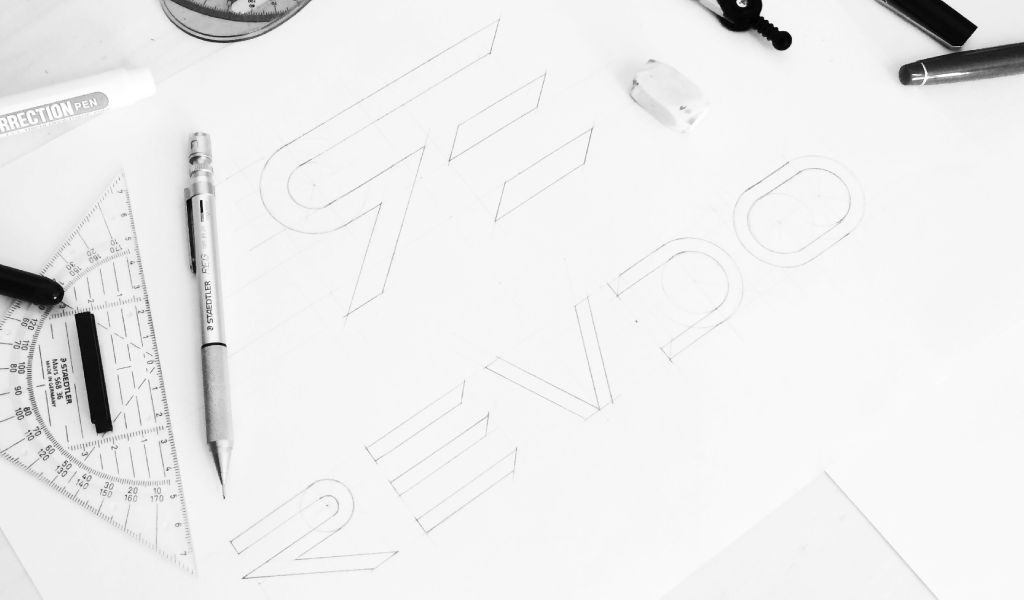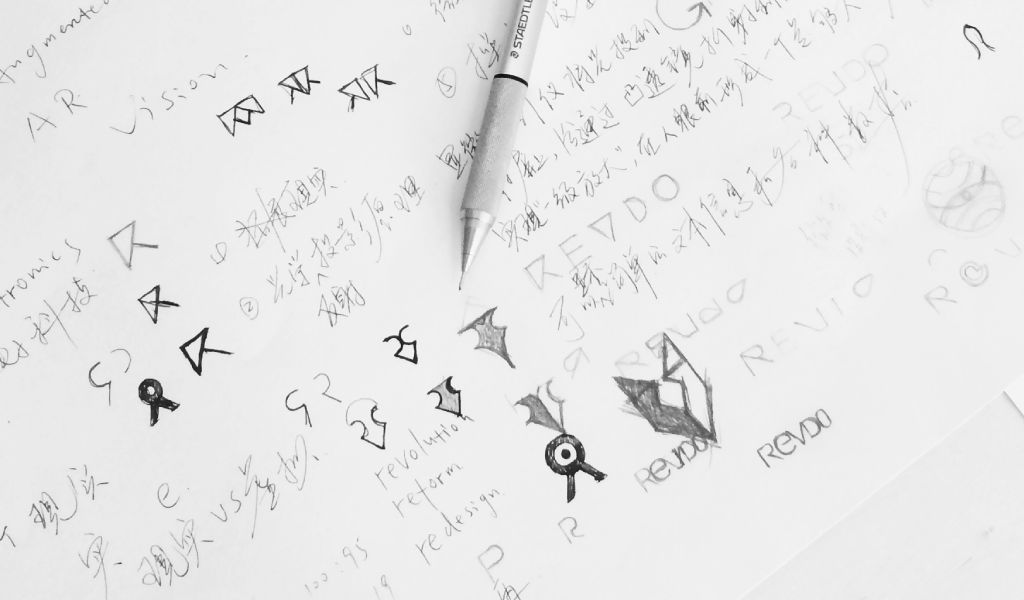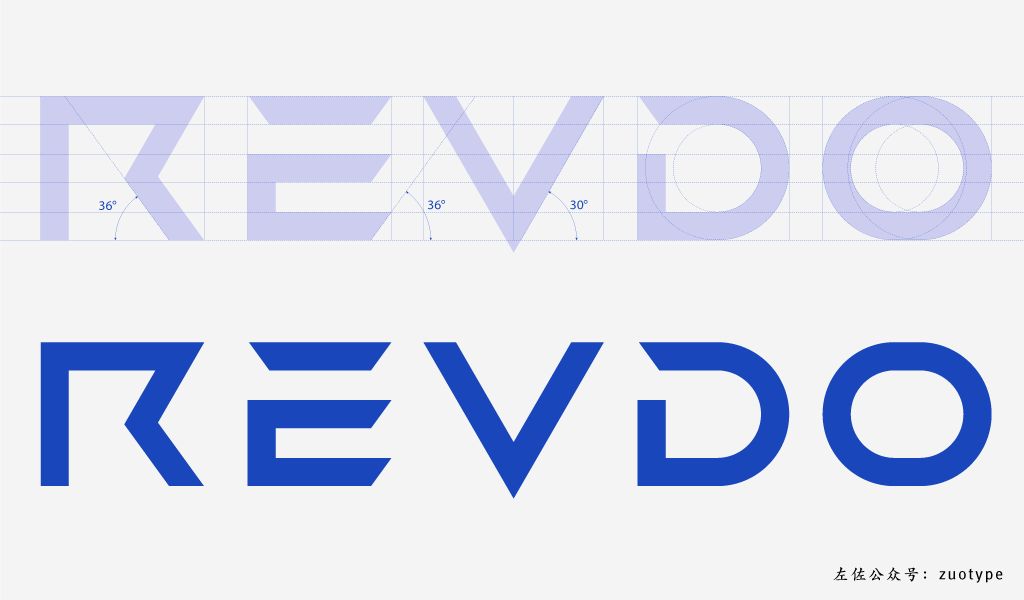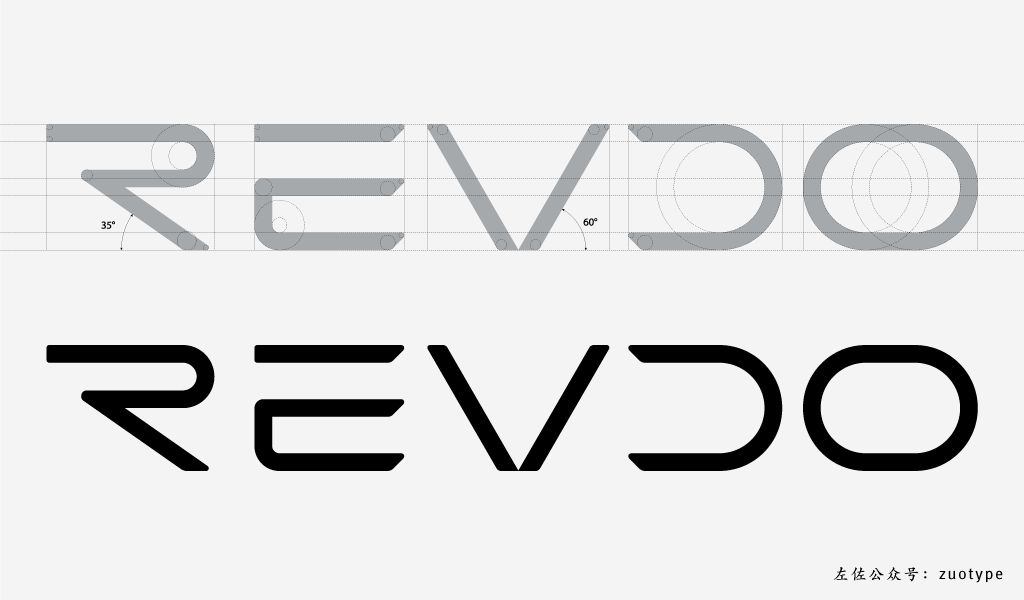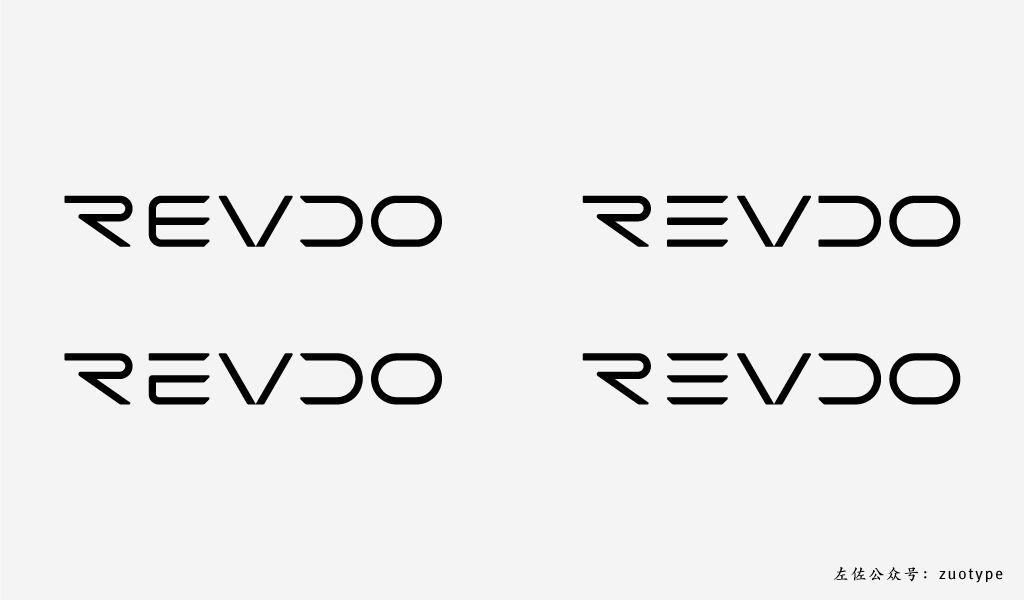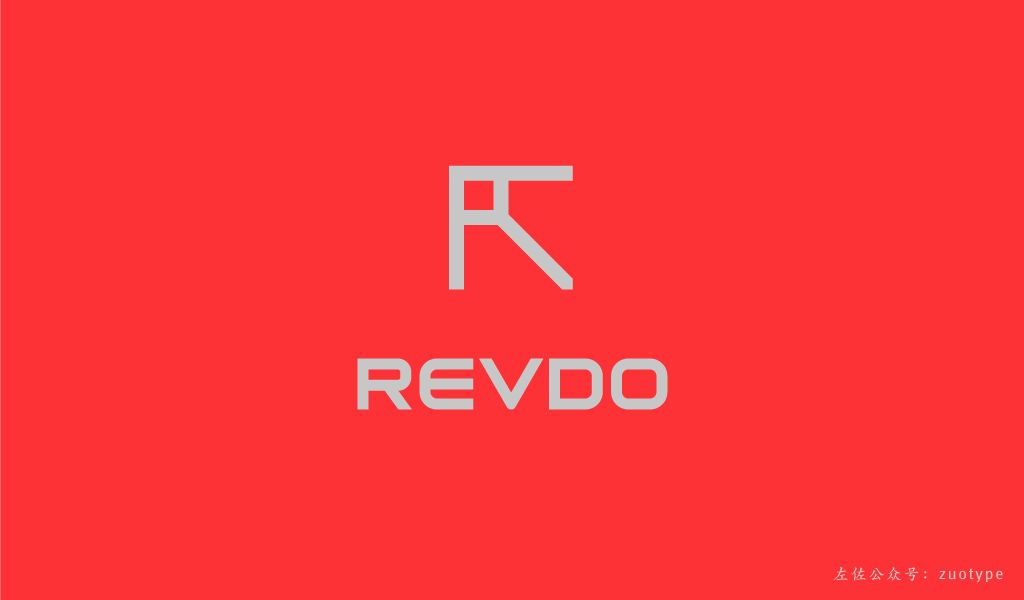
revdo,AR智能头盔品牌,抬头显示、后置摄像头、安卓系统等。rev是发动机每分钟的转速,re是重新设计的意思,do则是行动。
智能、科技、未来
从关键词出发,找到了一些横向领域的参考字形。比如美国头盔品牌Skully、谷歌眼镜GLASS、电影《安德的游戏》、美剧《星际迷航》等。
西文logo最常见的做法就是从首字母出发,结合关键词,联想名字带来的画面元素,或产品形的延伸,把这些信息通过字母这个载体传达出来。
从草稿里选择的几个方向,大前提是图形具有未来气质。类似这样简洁,且与智能相关的图形,我会在保证美观的前提下,尽量用数学去规范,因为任何科技最后都是数学。用“RE”的概念,重新定义、另一个方向,把“R”翻转,与“E”在形式上连接,并去掉各自的竖,形成一个新的图形元素。用“鲁宾杯”的负形手法,用互为镜像的“R”的外部空间,组合出一个新的图形元素,同样表达出重新定义、基于现在但又不同于现在的可能性。
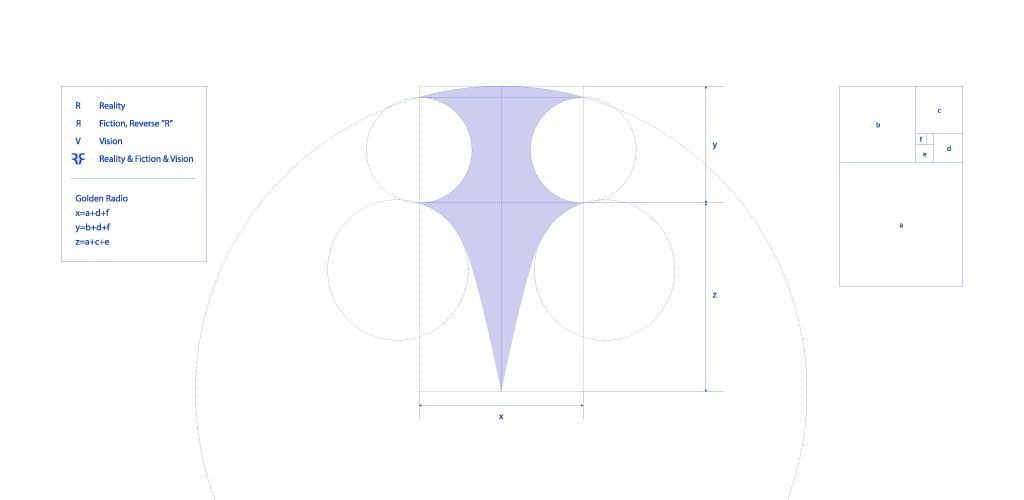
这个图形与特斯拉有些许类似,虽然之前并未参考,但对于简洁的图形来说,其实区别很明显,只是特斯拉太出名,最好还是规避一下,避免落人口实。所以降低了图形的高度,从深“V”变为圆领,视觉效果确实有折扣,所以宁可使用之前的版本。把技术上的现实增强,转化为抽象的图形,并与“R”结合,从一个小的方形,放大到一个大的方形空间,然后去掉边界,传达科技带来的无限可能性。什么样的西文具有未来科技感?一般来说,无衬线体,且是等线的,用几何图形组合而成,比如圆形、直线、直角等,然后字母有缺口、或有缺笔,字面偏扁,大写,不能过粗。
最直接的、最容易、最常见,但略带点复古,我管这种风格叫“诺基亚式”,《银翼杀手》《疯狂的麦克斯》《赛博朋克2077》可归于这一类。扁、圆角、中等粗细、等线。
之前在《机械姬》文章里提到过,常用小写字母,有温度,我管这种风格叫“仿生式”,《西部世界》《普罗米修斯》《异星灾变》可归为这一类。字母“e”用小写,且形式用螺旋线,字母“V”尖角变为平角。个性很强,适合单独作为logo,不太适合作为辅助来搭配图形。
一般以Futura字形为基础,字母有缺口或缺笔,用几何圆形或尖锐的角度绘制字形,大写,常规偏细,比如电影《遗落战境》里的字体,我管这种风格叫“太空式”,《太空漫游2001》《千钧一发》《无姓之人》可归于这一类。字母“R”做了很大变形,“ED”做了缺口处理,“O”从正圆,变为扁圆。
2、3相结合,得到的字形,圆角、缺口、省笔,我管这种风格叫“特斯拉式”,以流线型的跑车、高科技产品为代表。